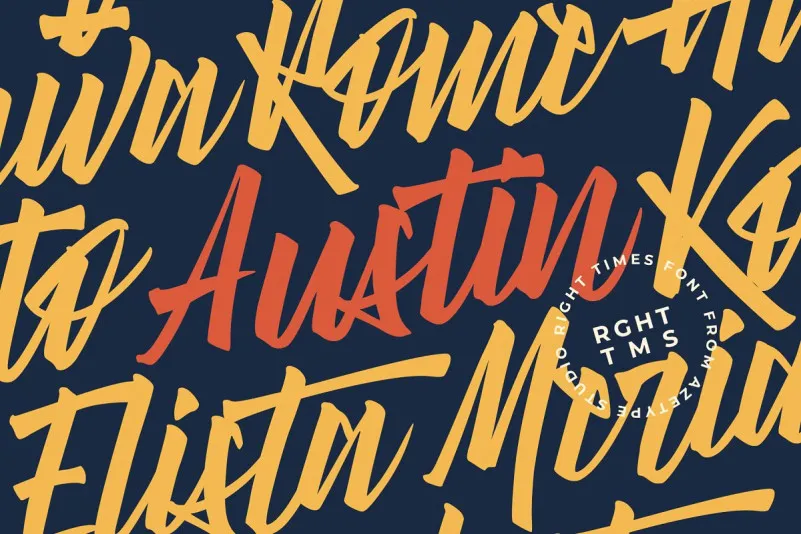
Right Times Brush Font – Download Grátis
O ‘Right Times Brush Font’ é uma fonte script criada pela 24Design que traz um toque original e único a seus projetos design. Esta fonte foi desenvolvida para artistas gráficos, designer de logotipos ou qualquer profissional do setor da moda que busca dar um aspecto encantador a suas criações com uma personalidade única. Com uma combinação cuidadosa dos caracteres, o ‘Right Times Brush Font’ oferece uma opção versátil para os designers em sua paleta de ferramentas digitais, adaptando-se perfeitamente tanto ao trabalho individual quanto aos projetos institucionais. Perfeito para trabalhos como cartazes, criações de marca pessoal e materiais promocionais, a ‘Right Times Brush Font’ é uma escolha ideal que vai deixar seu design brilhar com um toque autêntico. Sua versatilidade torna-a uma excelente adição à sua coleção de fontes para todas as suas necessidades gráficas.